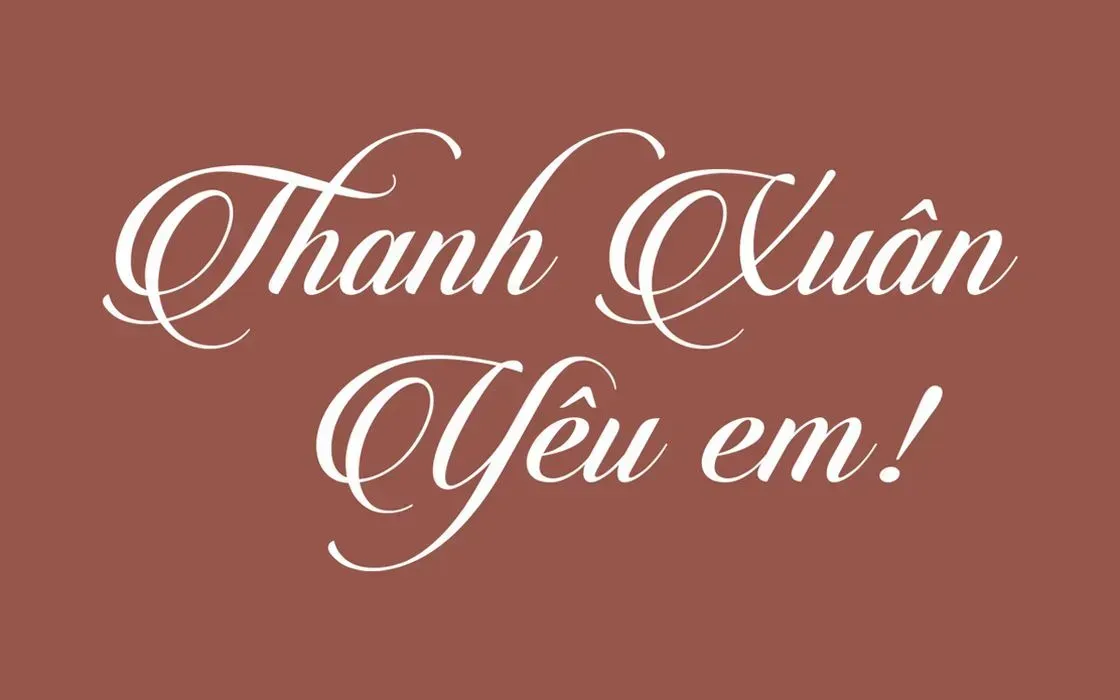
Font chữ mềm mại, thanh lịch UVF Candlescript Pro Việt hóa
UVF Candlescript Pro là một font chữ viết tay (script) mang phong cách nghệ thuật, mềm mại và lôi cuốn, nổi bật với các đường nét uốn lượn duyên dáng, thanh thoát và đầy chất thơ. Font mô phỏng nét bút lông cổ điển, kết hợp với sự uyển chuyển mượt mà giữa các ký tự, tạo nên cảm giác tự nhiên, lãng mạn nhưng vẫn sang trọng và chuyên nghiệp.
Từng ký tự trong Candlescript Pro có độ đậm vừa phải, cấu trúc chặt chẽ nhưng vẫn bay bổng, phù hợp cho những thiết kế đề cao cảm xúc, sự nữ tính và tính cá nhân hóa cao. Đây là font lý tưởng cho:
– Logo mỹ phẩm và thời trang nữ
– Thiệp cưới, thư mời, tiêu đề blog
– Bao bì sản phẩm handmade hoặc cao cấp
– Các thiết kế mang tính nghệ thuật, lãng mạn
Font gốc Candlescript Pro được thiết kế bởi Måns Grebäck, một nhà thiết kế nổi tiếng với nhiều bộ font viết tay tinh xảo. Font này còn được yêu thích vì hỗ trợ nhiều ligatures (kết nối chữ cái) giúp văn bản hiển thị như được viết thật – mượt mà và liền mạch.
Phiên bản Việt hóa bởi UVF (Ước Việt Fonts) đã được tinh chỉnh kỹ lưỡng, bổ sung đầy đủ dấu tiếng Việt, giữ nguyên phong cách uốn lượn thanh thoát của bản gốc, đồng thời đảm bảo khả năng tương thích với các phần mềm như Photoshop, Illustrator, Canva, InDesign…
Nếu bạn đang tìm một font viết tay mềm mại, lãng mạn và sang trọng, UVF Candlescript Pro chính là lựa chọn hoàn hảo để tôn lên vẻ đẹp cảm xúc và nghệ thuật trong mọi thiết kế mang dấu ấn cá nhân.